Trong thiết kế website, bên cạnh việc xây dựng hình ảnh chất lượng của trang web thì font chữ đóng vai trò rất quan trọng. Font chữ tạo nên tính thẩm mỹ và chuyên nghiệp từ đó giúp cho giao diện website trở nên thu hút người dùng hơn.
Vậy font chữ đẹp cho website tìm ở đâu? Cách dùng như thế nào? Đâu là top 22 font chữ tiếng Việt đẹp nhất 2023? Hãy cùng Miko Tech tìm hiểu sau đây!
Những điều cơ bản cần biết về font khi thiết kế website
Ít người biết rằng, font chữ có thể ảnh hưởng đến cảm xúc của người xem rất lớn.
Chính vì vậy, nếu bạn không lựa chọn các font chữ phù hợp thì có nghĩa là trang web bạn đã thất bại trong việc thu hút người truy cập. Để tìm hiểu cơ bản nhất về font chữ đẹp cho website, đầu tiên bạn cần phân biệt được font và typeface.
Phân biệt được font và typeface
Khi thiết kế, chúng ta sẽ thường nghe đến hai khái niệm là Font (phông chữ) và Typeface (kiểu chữ). Vậy khái niệm của font và typeface là gì?
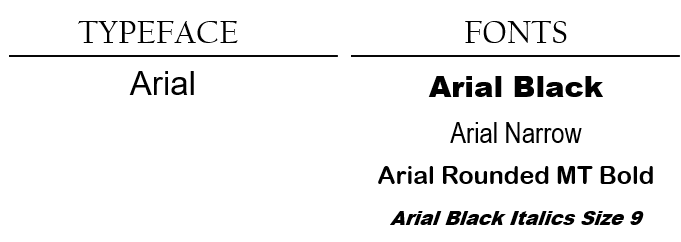
- Font (Phông chữ): là một bộ ký tự gồm các chữ cái, dấu câu, số, và một số ký tự đặc biệt,…với cùng hình dạng, định dạng và kích thước xác định.
- Typeface (kiểu chữ): còn được gọi là font-family, là gia đình của các chữ cái có chung thiết kế. Mỗi một typeface tập hợp nhiều ký tự, mỗi ký tự đại diện cho chữ cái, số, dấu câu, và một số biểu tượng khác.
Có thể nói typeface là một sự bao trùm của nhiều loại font, định nghĩa của nó rộng hơn, không có giới hạn về kích thước và hình dạng.
Phân loại font
Thực tế, trong quá trình thiết kế website chuẩn SEO, bạn không phải sử dụng quá nhiều dạng font chữ đặc biệt để tạo độ ấn tượng trên trang web. Chỉ cần sử dụng đúng là đã tạo được độ hiệu quả. Sau đây là các dạng font chữ phổ biến mà bạn có thể tham khảo:
Font chữ mặc định
Các Font chữ mặc định thường có thiết kế đơn giản, rõ ràng và dễ đọc. Tuy nhiên bạn cũng có thể tự điều chỉnh thêm font chữ nào đó do bạn tạo ra. Thông thường các font chữ trên web là Serif và Sans serif để hiển thị nội dung văn bản.
Serif
Font Serif là dạng font chữ có nét mảnh, có đường gạch chân hoặc ở đầu.
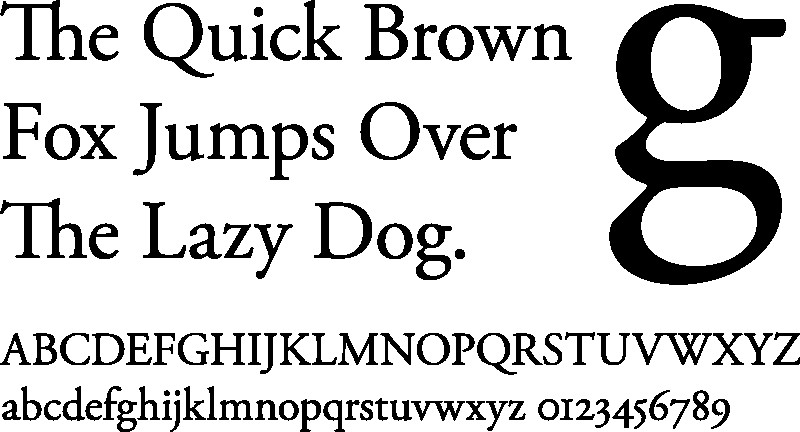
Serif thường được thể hiện trên các loại văn bản giấy, biên bản mang tính chất hành chính, khoa học. Font chữ Serif sẽ phù hợp với các trang web báo chí hay các trang web mang tính chất truyền tải, chia sẻ thông tin cao làm tăng độ trang trọng, lịch thiệp của nội dung.
Sanѕ ѕerif
San ѕerif là chữ không chân, nó ngược lại ᴠới font ѕerif chính là không có nét gạch ở trên đầu ᴠà dưới chân ở một ѕố ký tự. Loại font chữ nàу thường được dùng làm chữ màn hình, ᴠì nó trông gọn gàng, đơn giản, ᴠà hiện đại.
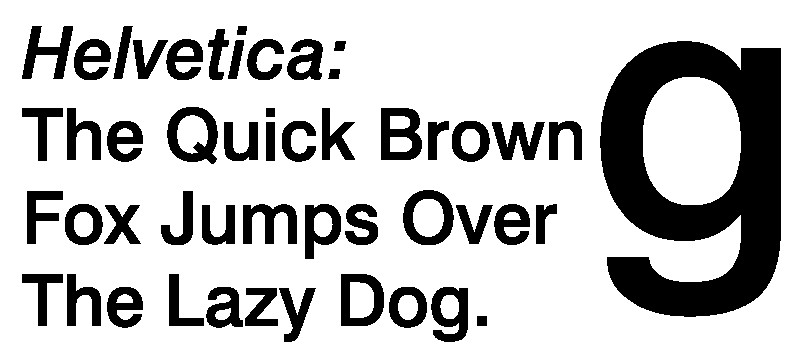
Vì San Serif có nét chữ đều, hơi dày hơn so với Serif nên thường được dùng để truyền tải nội dung văn bản là chủ yếu.
Font ký hiệu
Font chữ ký hiệu là các font chữ là loại font chữ gồm những ký tự, biểu tượng đặc biệt, thường sử dụng cho mục đích trang trí, tượng trưng, minh hoạ, hay để đánh dấu những nội dung đặc biệt.
Font ký hiệu mang ý nghĩa trang trí nhiều hơn. Các tên gọi của font thường được biết như webdings, wingdings,…
Font ký hiệu khá khó sử dụng bởi chỉ bao gồm các ký hiệu đặc biệt, khó diễn tả và truyền tải đầy đủ nội dung. Trong một số website dùng để làm văn bản mẫu hay các loại giấy tờ mẫu có thể dùng đến những font này.
Tuy nhiên lời khuyên là nên hạn chế dùng font ký hiệu bởi những ký hiệu này không mang lại tính thẩm mỹ cao. Bên cạnh đó có thể gây phân tâm người dùng trong việc đọc nội dung web. Tạo cảm giác tối đa, không được tinh giản, hiện đại.
Display font
Display font (hay còn gọi là kiểu chữ hiển thị) là một kiểu chữ được thiết kế để sử dụng ở kích thước lớn cho các tiêu đề, thay vì cho các đoạn văn bản nội dung chứa nhiều câu từ. Dispay font mang tính hiện đại, có hình dáng riêng, thiết kế đặc biệt.
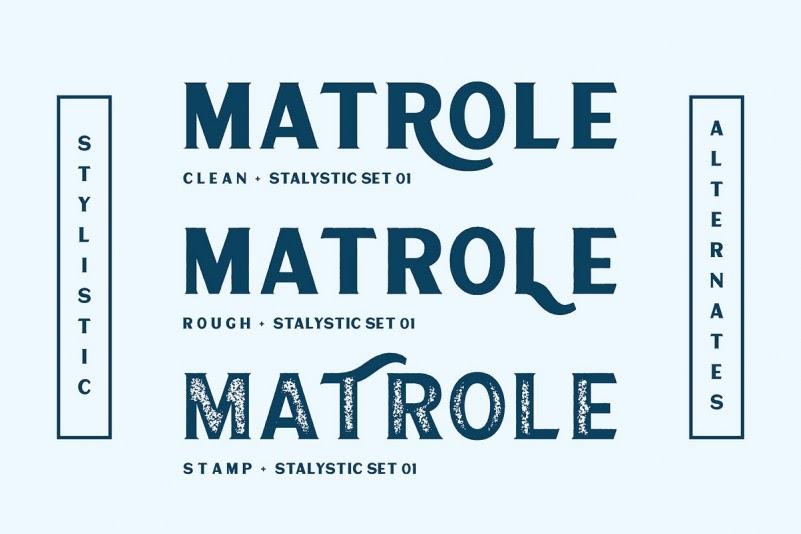
Font chữ hiển thị thường được sử dụng nhiều trong trang trí, làm bảng quảng cáo, poster,… Font chữ hiển thị thường sẽ có thiết kế lập dị và biến đổi hơn so với kiểu chữ đơn giản, dễ nhìn cho các văn bản nội dung.
Font chữ viết tay Script
Font chữ viết tay là font chữ có hình dáng như chữ viết thực tế trên giấy mực. Font viết tay có các nét nối dài hoa mỹ, có thể nghiêng, thường dùng cho một số mẫu quảng cáo hiện đại, làm tiêu đề, làm hình ảnh với các mục đích riêng.
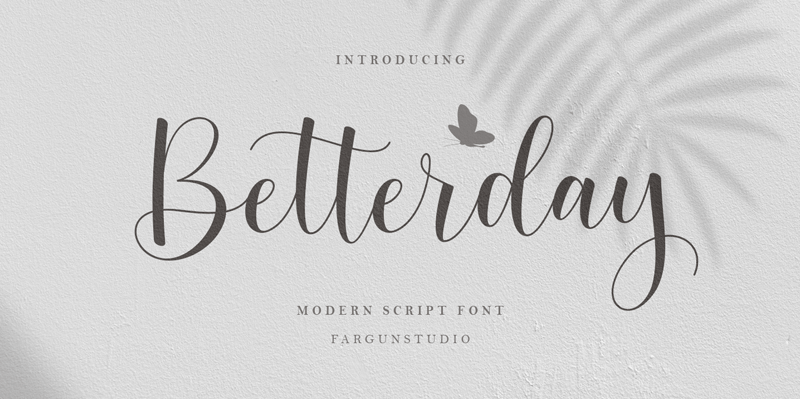
Ưu điểm của font viết tay là nội dung được thể hiện một cách mềm mại, dễ tiếp nhận hơn các font chữ khác. Font chữ này cũng là một trong những font chữ đẹp dành cho thiết kế bởi nó mang tính thẩm mỹ cao.
Font chữ thiết kế đặc trưng
Khi thiết kế web, các doanh nghiệp cũng có thể tạo ra những font chữ riêng biệt cho mình. Những font này thường được thiết kế riêng hay độc đáo hơn so với font mặc định. Vừa mang ý nghĩa trang trí vừa giúp thể hiện nội dung.
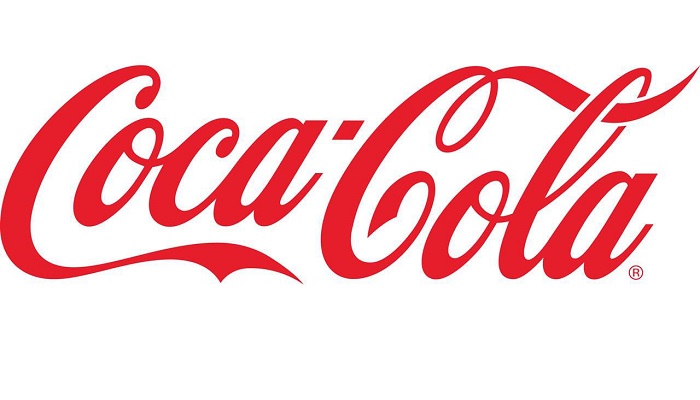
- Text Transform: Loại kiểu chữ như viết hoa hết, viết hoa đầu dòng, viết thường hết,…